싸인을 처음 만들 때 가장 중요한 것은 ‘연습’이요. 멋진 싸인을 원 한다면 여러 가지 방법을 시도하며 손에 익히는 과정이 필수랍니다.
많은 사람들이 처음부터 완벽한 싸인을 만들려고 하지만, 사실 싸인 은 여러 번 시도해 보면서 점점 다듬어 나가는 게 중요해요. 연습을 통해 자신만의 개성을 담을 수 있어야 하거든요.
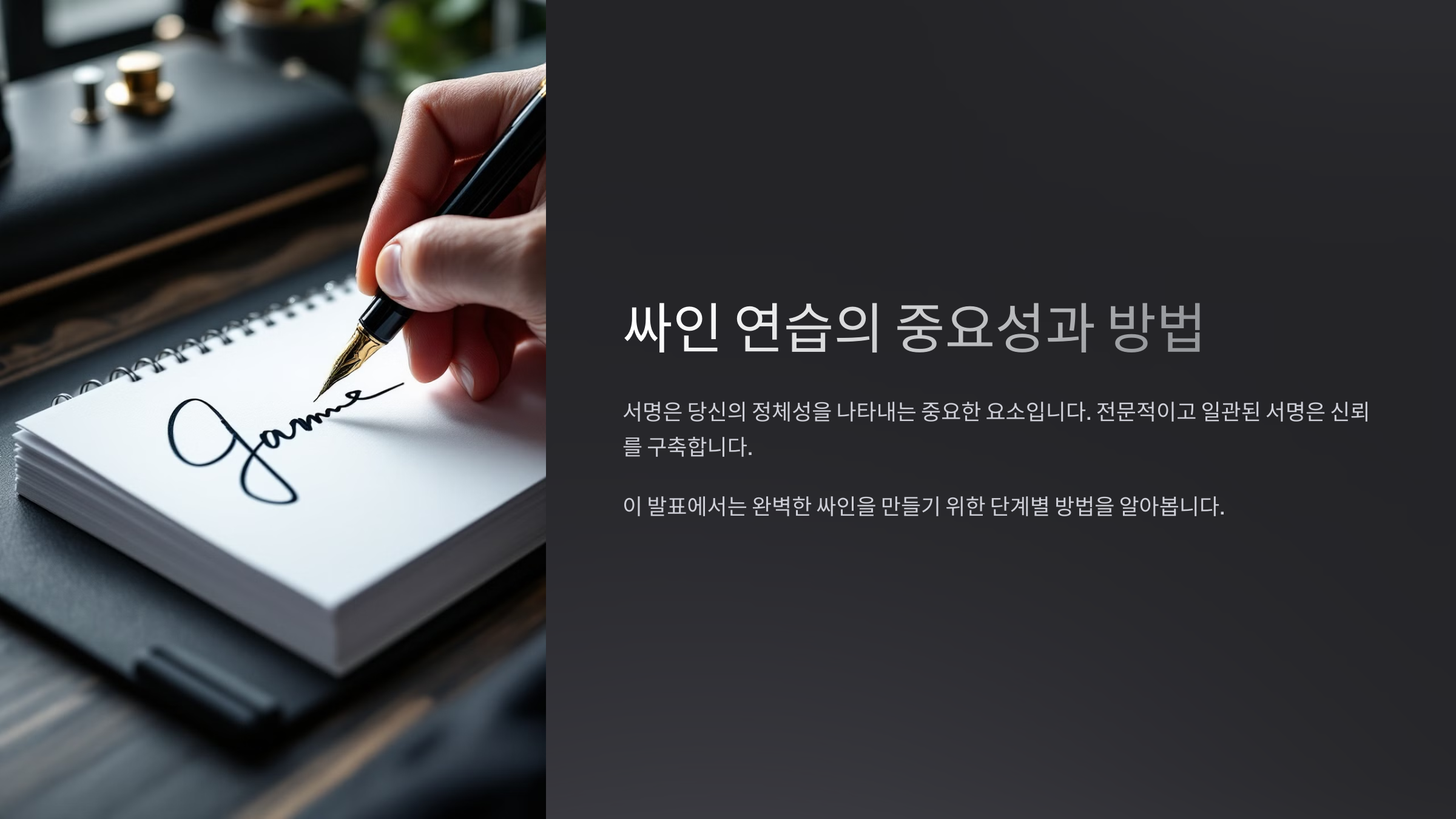
내가 생각했을 때, 싸인은 단순한 글씨가 아니라 ‘나를 나타내는 하나 의 예술’이예요. 그래서 연습을 할 때도 단순히 쓰는 것이 아니라, 스타일을 연구하면서 나만의 싸인을 찾아가는 과정이 필요해요. ✨
싸인 연습이 중요 한 이유
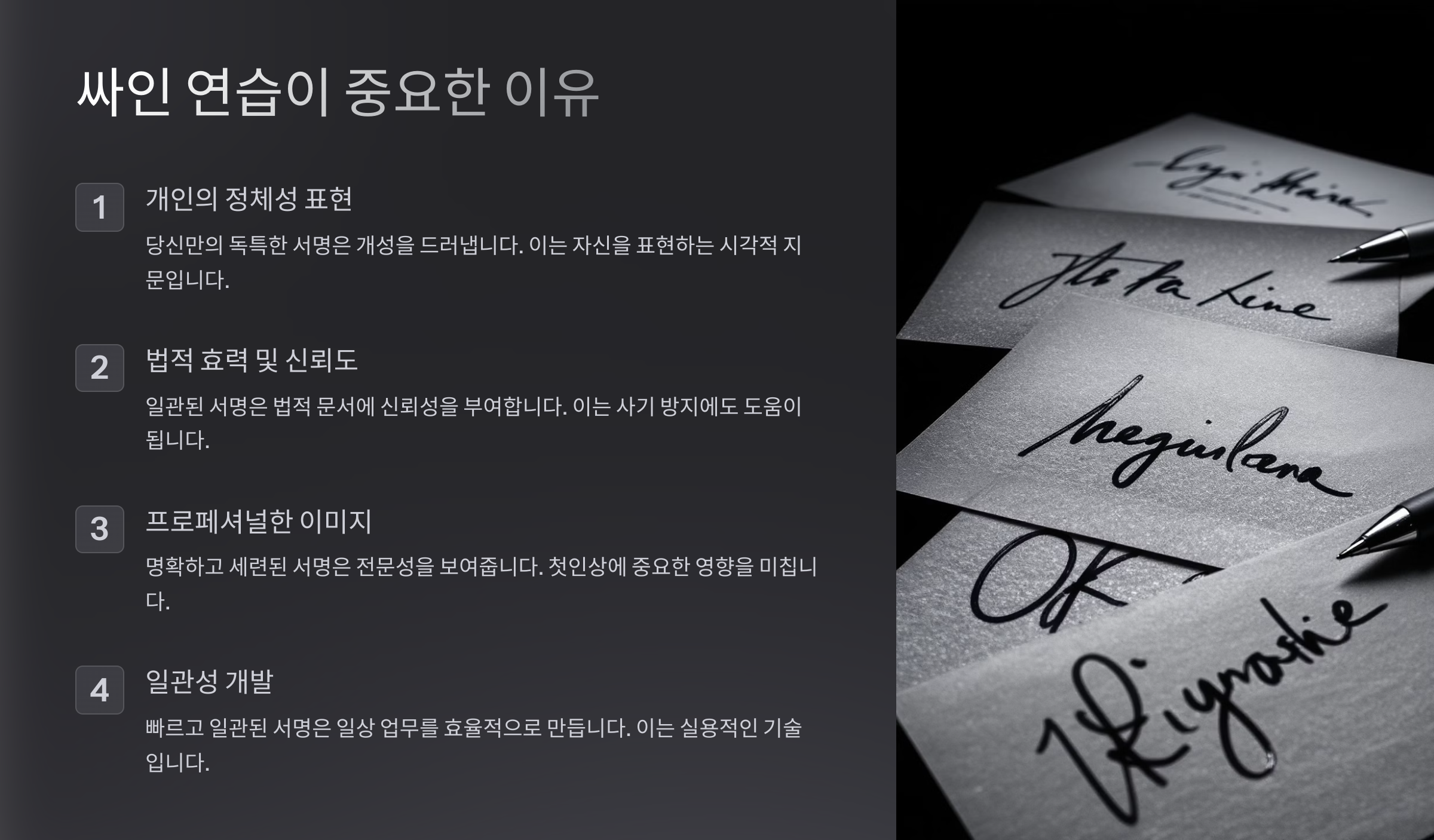
싸인을 연습하는 이유는 단순히 글씨를 잘 쓰기 위해서가 아니예요. 나만의 개성 있는 스타일을 만들고, 손에 익숙하게 하기 위해서죠. ✍
특히 공식 문서나 계약서에서 사용하는 싸인은 자주 쓰게 되기 때문 에, 자연스럽고 빠르게 쓸 수 있어야 해요. 연습 없이 만든 싸인은 시간이 지나면 변형될 가능성 이 크기 때문에 꾸준한 연습이 필수랍니다!
싸인 연습이 중요한 이유
이유 설명 자연스 러움 연습하 면 싸인이 손에 익어 자연스럽게 써짐 일관성 항상 같은 형태로 유지할 수 있음 개성 자신만 의 스타일을 확립할 수 있음 이제 기본적인 싸인 연습법을 알아볼까요? ✍
기본 적인 싸인 연습법
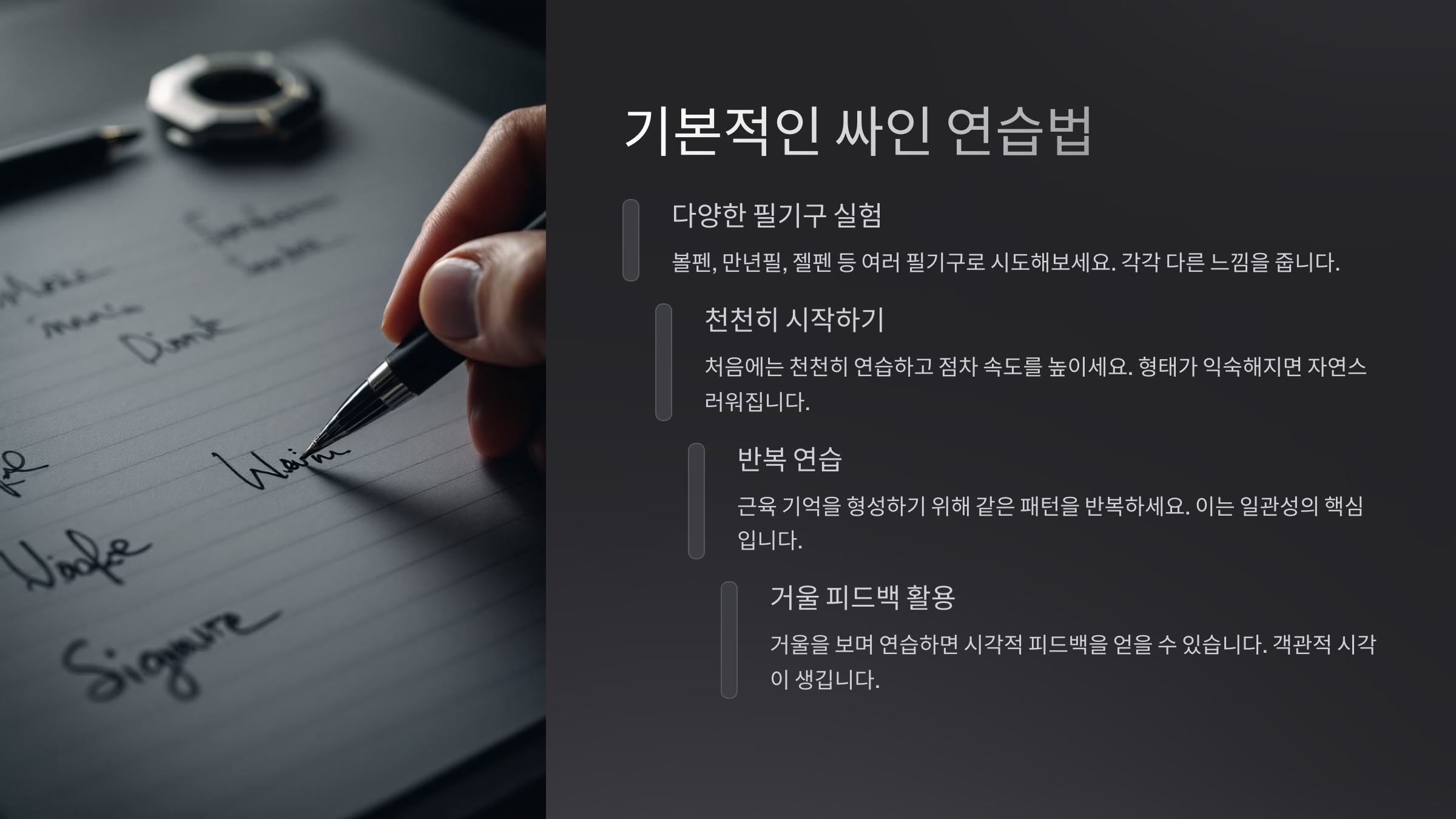
싸인을 처음 만들 때는 너무 복잡한 디자인을 시도하기보다는, 기본적인 형태를 익히는 것이 중요해요. ✍
처음에는 종이에 여러 스타일로 자신의 이름을 적어보는 연습부터 시 작하세요. 필기체, 대문자, 이니셜 등 다양한 방식으로 써보면서 어떤 스타일이 가장 마음에 드는지 확인하는 것이 좋아요.
기본 연습 방법
연습 방법 설명 이름 여러 번 써보기 다양한 크기와 스타일로 연습 초성만 활용 예: 김 지훈 → KJH 필기체 연습 영어나 한글 필기체 연습 기본적인 연습을 마쳤다면, 이제 다양한 스타일을 실험해보는 단계로 넘어가 볼까요?
다양 한 스타일 실험하기
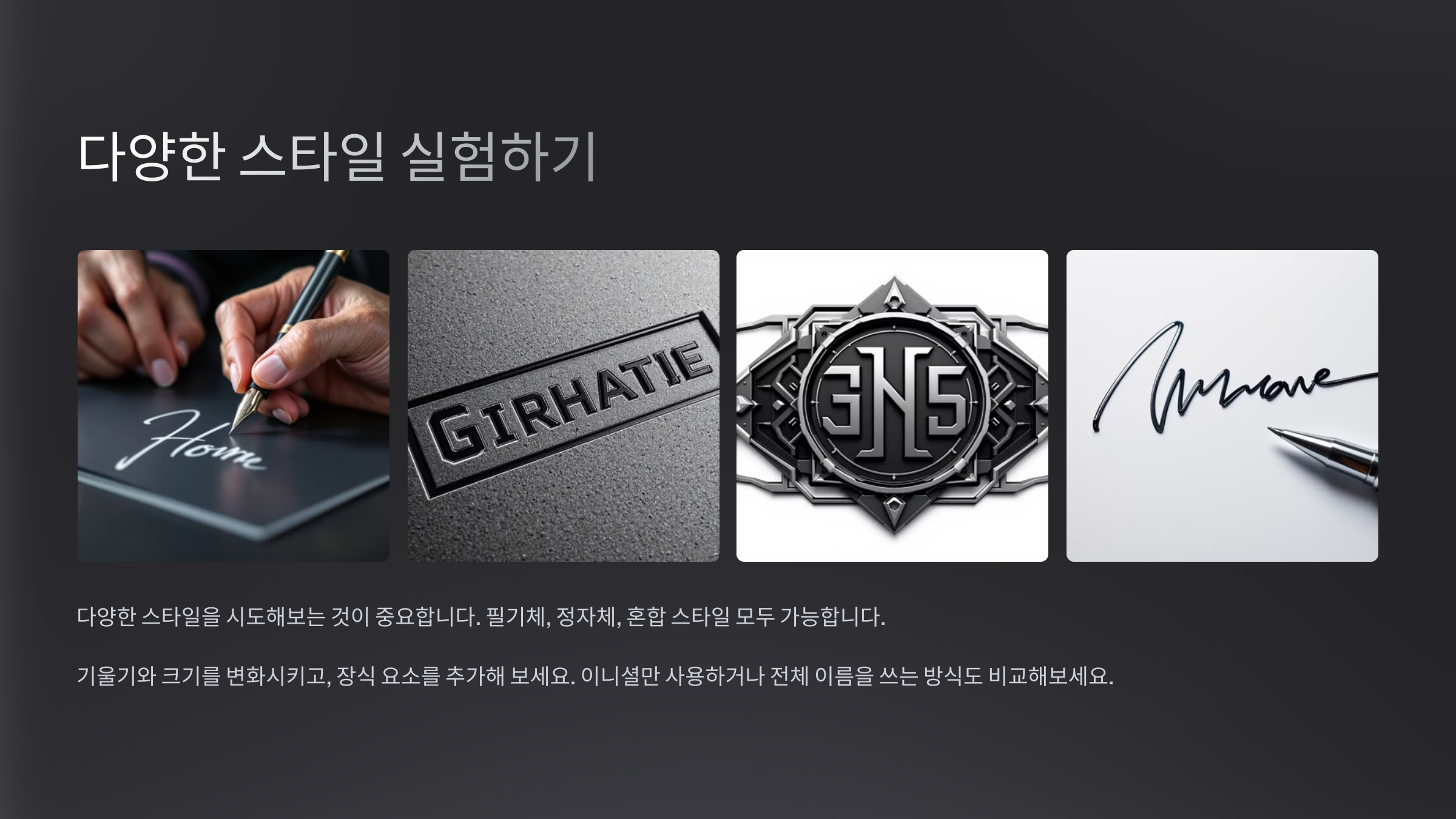
싸인의 개성을 더욱 살리고 싶다면, 여러 가지 스타일을 시도해보는 것이 중요해요.
예를 들어, 대문자와 소문자를 조합하는 방법, 이니셜만 활용하는 방법, 선과 곡선을 강조하는 방법 등이 있어요. 이런 다양한 스타일을 테스트하면서 나만의 싸인을 찾아보세요!
다양한 싸인 스타일
스타일 특징 대문자 스타일 예: KIM JI HOON 이니셜 스타일 예: KJH 곡선 강조 부드러 운 곡선을 활용한 싸인 이제 싸인의 느낌을 더욱 살릴 수 있는 필압 조절법도 배워볼까 요?
필압과 선 굵기 조절법
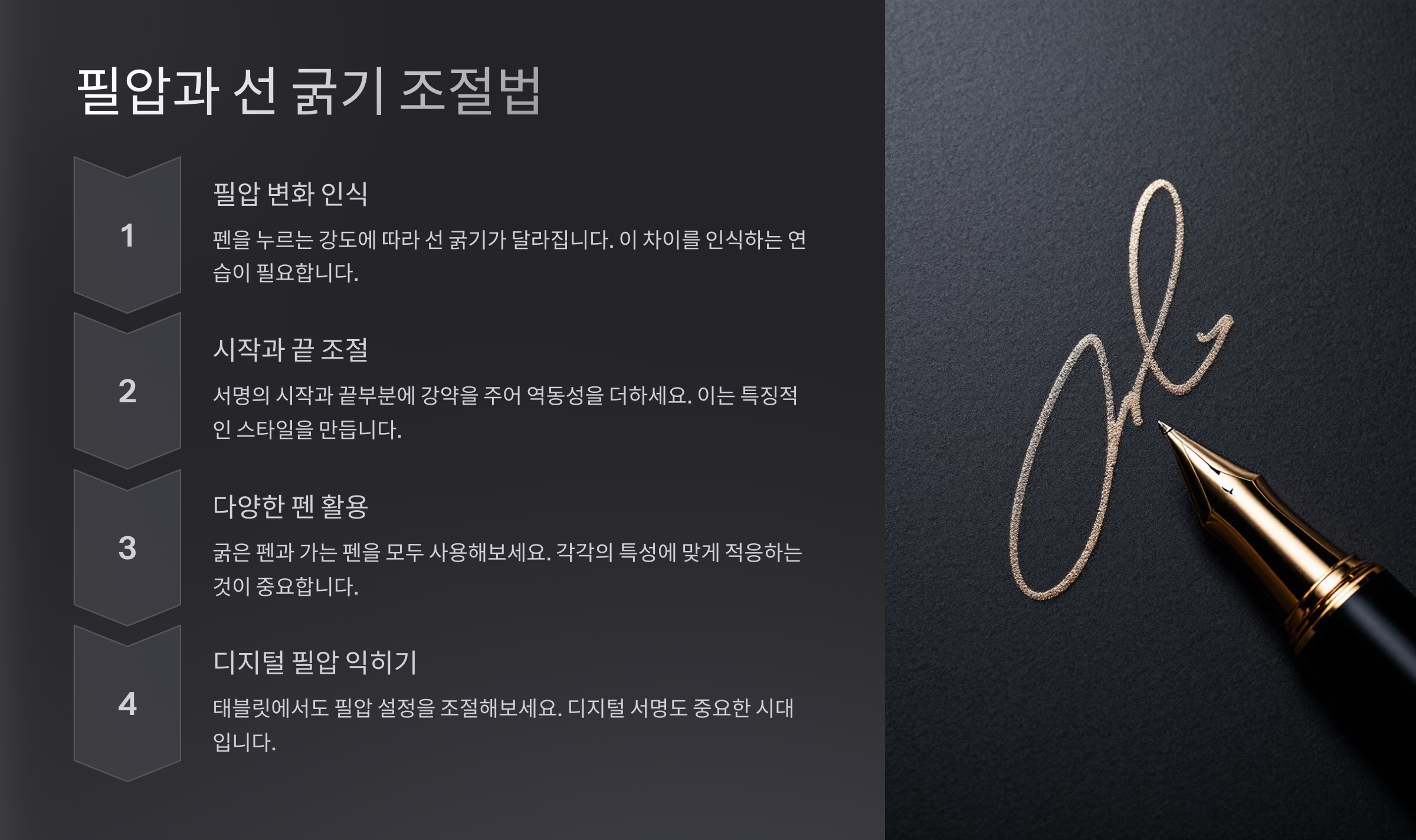
싸인의 강렬함을 살리기 위해서는 필압과 선의 굵기 조절이 중요해요. ✍
필압을 조절하면 싸인의 강약을 조정할 수 있어 더욱 세련된 느낌을 줄 수 있어요. 예를 들어, 이름의 첫 글자를 강하게 쓰고, 끝부분을 부드럽게 마무리하면 더 멋스러워 보인답니다!
FAQ ❓
Q1. 싸인을 연습할 때 필기구는 어떤 게 좋을까요?
A1. 만년필이나 싸인펜처럼 필압 조절이 쉬운 펜을 사용하는 것이 좋 아요.
Q2. 싸인을 연습하는데 시간이 오래 걸릴까요?
A2. 개인차가 있지만, 꾸준히 연습하면 금방 손에 익어요. 하루 10분 씩 연습해 보세요! ⏳